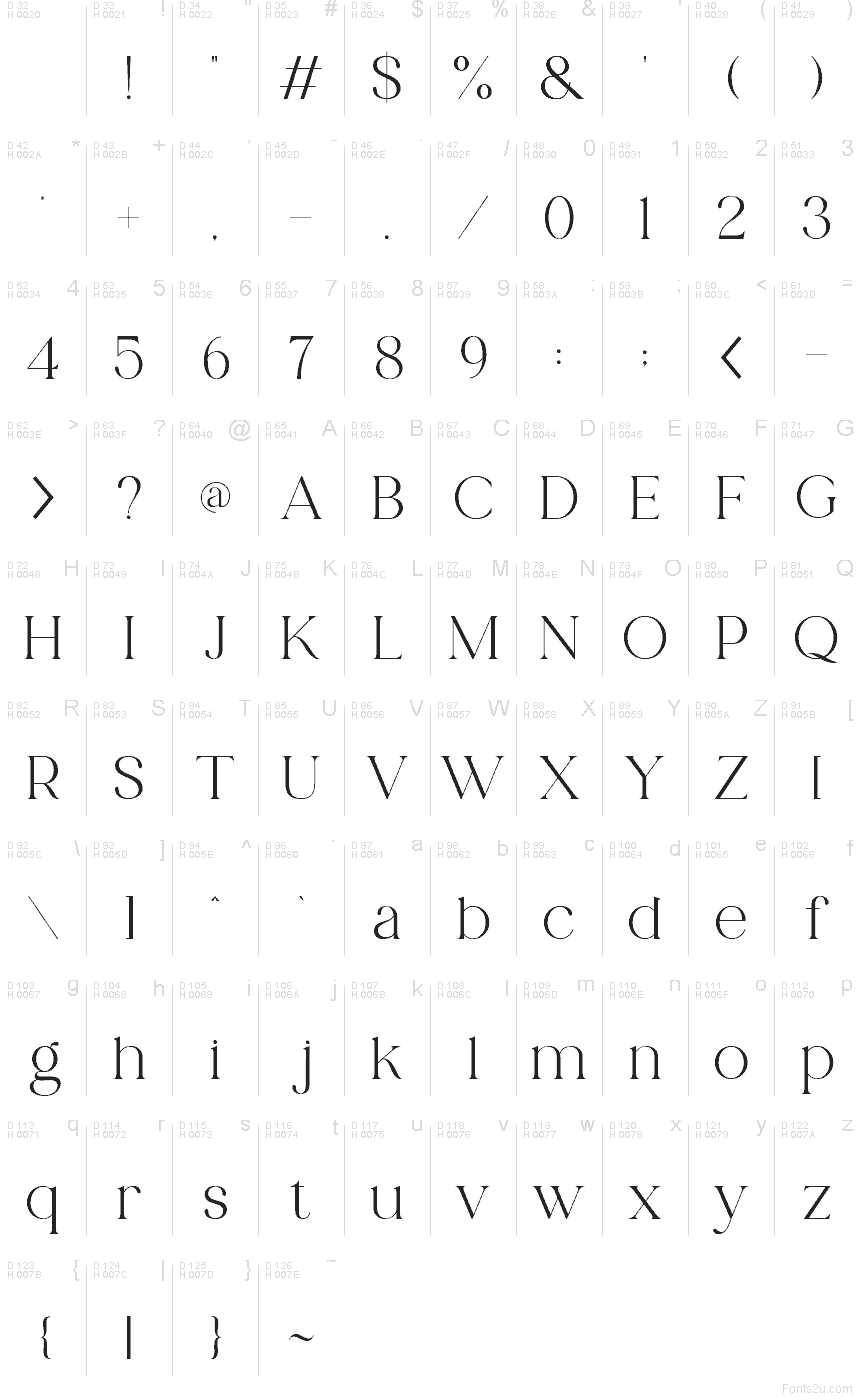
Triklen Care, da Ermedia Studio, é uma fonte serifada gratuita de alto contraste, com traços ultrafinos, curvas amplas e uma diferença marcante entre hastes grossas e finas. Formas arredondadas e terminais curvados suavizam os vértices pontiagudos e as proporções altas e verticais.
Para marcas de moda e beleza, essa combinação de precisão e sinuosidade faz dela uma escolha convincente para embalagens de perfumes ou para a identidade visual de uma boutique. Ela também funciona bem em títulos de revistas de moda e convites para eventos formais, especialmente para clientes que buscam o refinamento das fontes serifadas tradicionais para exibição, mas com uma presença geral mais leve e delicada.